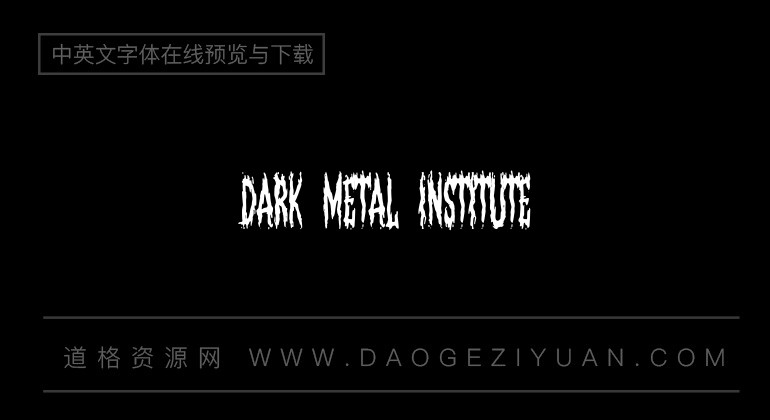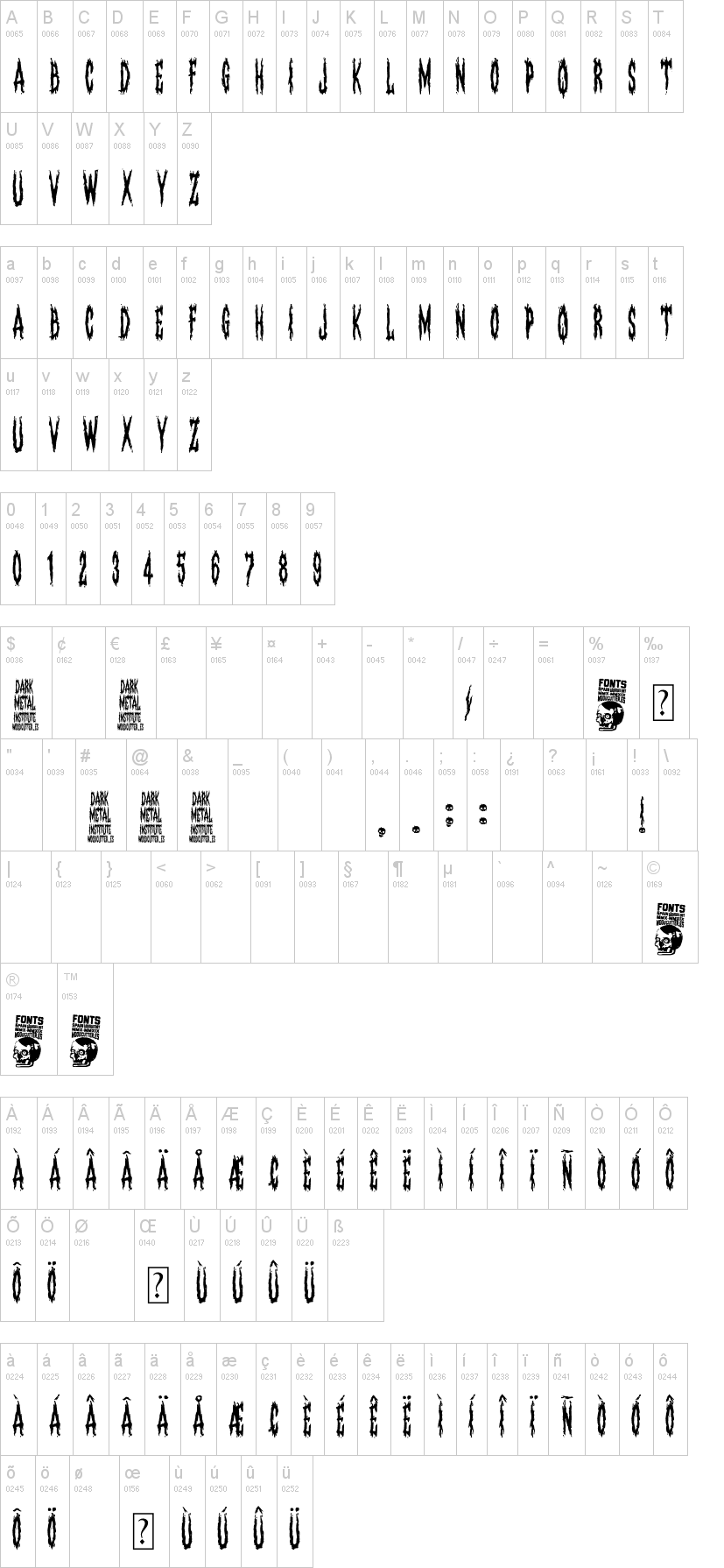
Dark Metal Institute
Dark Metal Institute字体是一款粗体、抗锯齿的复古风格字体,适合用于招牌、标识、标题等场景。它的特点是粗体、抗锯齿,字体线条细腻而充满力量,可以带来一种粗犷、激进的视觉效果。它的字体设计非常精美,可以给人以古朴、简洁的感觉。它的主要应用场景是用于建筑物、标识、标题等场景,可以带来一种沉稳、粗犷的视觉效果。
Dark Metal Institute是一款非常不错的手写艺术字体,具有很好的视觉感,适合于文化类的宣传设计、商业类品牌的广告和产品包装设计以及个性化文字排版等较多场景。
Dark Metal Institute字符映射图